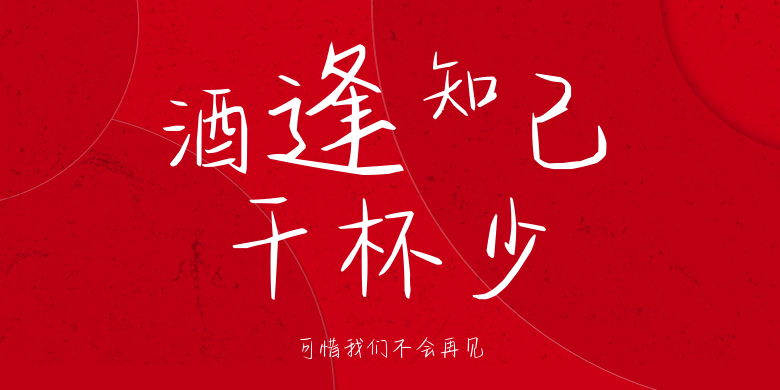
可惜我们不会再见
可惜我们不会再见,这款字体结构工整、笔画清晰,兼顾美观与易读性,适用于标题、正文、海报、包装、LOGO 等多种场景。字形优雅稳定,风格百搭耐看,适配日常排版与创意设计,让文字呈现更舒适、更具质感。可惜我们不会再见一笔一画,皆是细节,以均衡的比例、流畅的线条打造舒适视觉体验,字形端正大气,风格简约现代。无论是商业设计、品牌宣传还是日常排版,都能轻松驾驭,让文字更有格调与力量。可惜我们不会再见字体下载。